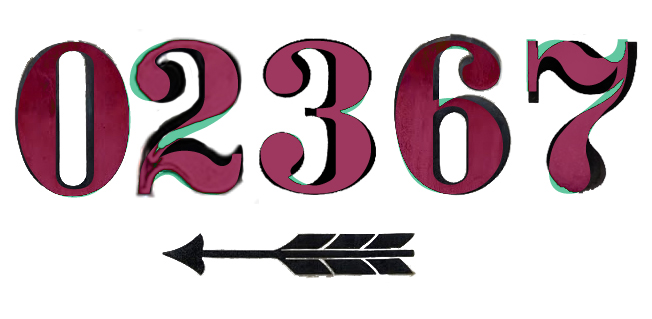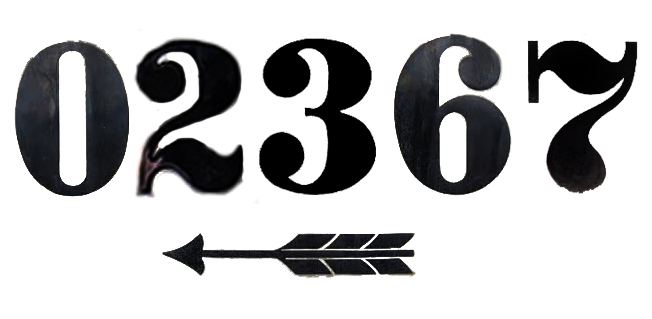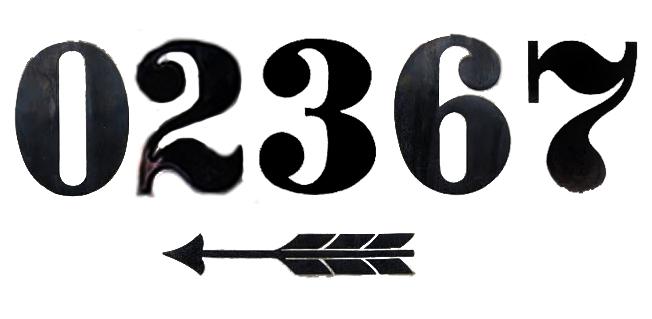
„Berliner Hausnummer“ (Emailleschild)
Ich bin auf der Suche nach der Schrift, wie sie in Berlin für die emaillierten Hausnummernschilder genutzt wurden.
Die Anbieter, die derzeit Emailleschilder anbieten, nutzen offenbar andere Schriften.
Folgende Zahlen kann ich anbieten:
What Font is brachte als Ergebnis u.a. Stencil Solid, die zwar auch sehr ähnlich ist, aber leider auch nicht passt. Außerdem sieht die 9 nicht schön aus (ich benötige die 94).
Die Fette Fraktur geht auch in die Richtung, ist aber zu „rund“.
Exakt diese Schrift zu finden, stelle ich mir wegen der Handarbeit des Schildermacher schwierig bis unmöglich vor. Wenn Du nach Bodoni oder Didone bei myfonts suchst, findest du viele Schrifte jener Geschmacksrichtung.
ich gehe davon aus, dass die Vorlagen handgeplasen und mundgemalt sind. Diese Ziffern findet man aber auch in vielen anderen Ecken von Deutschland. Ich biete eine Inflex als möglichen, aber nicht ganz perfekten Kandidaten an ...
Ich habe die Inflex bei Whatfontis nochmals „identifizieren“ lassen und bin dabei auf die Youbilee von Peter Wiegel gestoßen. Leicht verzerrt passt sie für meine Zwecke recht gut.
Hi! Konntest Du denn einen Schildermacher ausfindig machen, der den richtigen Font oder zumindest einen ännlichen verwendet?!
Nein. Nur dutzende, die ähnliches anbieten, teilweise sogar als Berliner Version, aber dann war es doch nur irgendeine Bodoni.